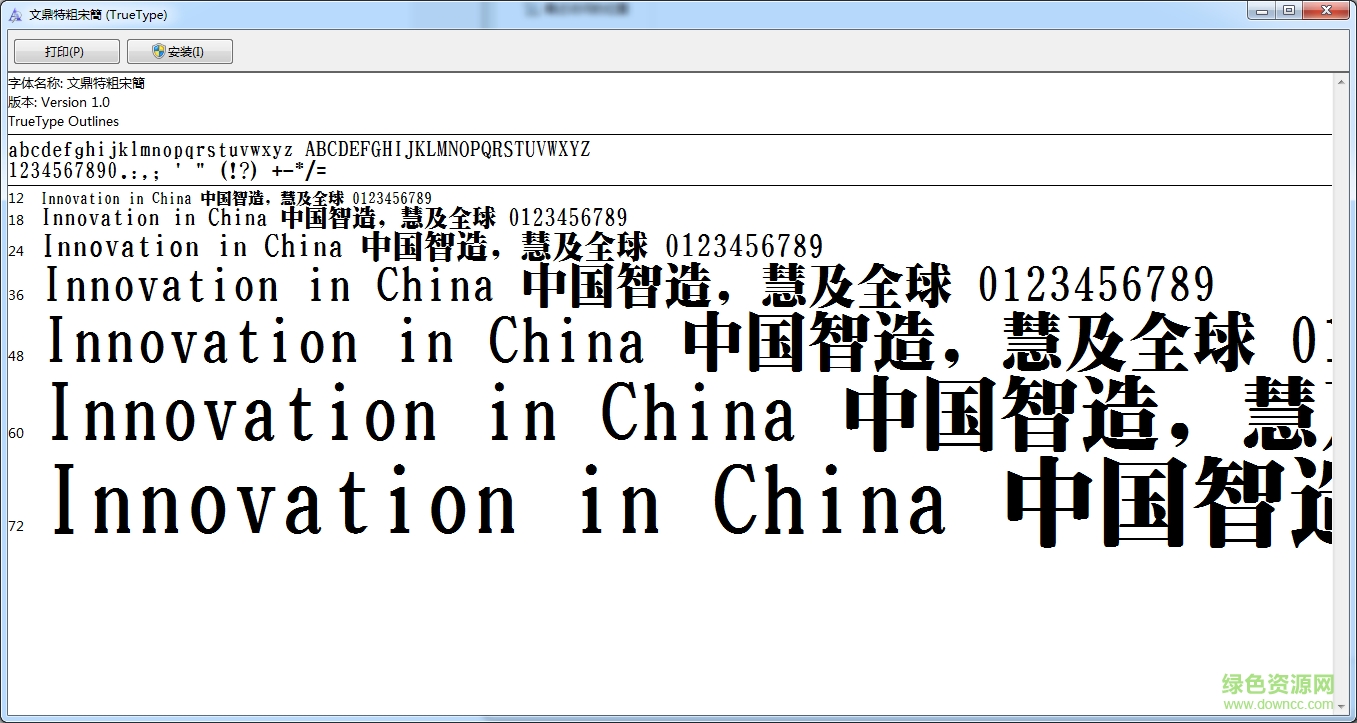
sungtieg ultra gb是什么字體?sungtieg ultra gb 字體就是文鼎特粗宋簡(jiǎn)的英文簡(jiǎn)寫,這款字體結(jié)合了黑體和宋體的共同特點(diǎn),筆畫粗壯,橫細(xì)豎粗,形體干練,閱讀性強(qiáng)!
sungtieg ultra gb是一款專門用于大字報(bào)方面的字體,比如報(bào)紙或雜志的頭條都可以使用到這款字體。